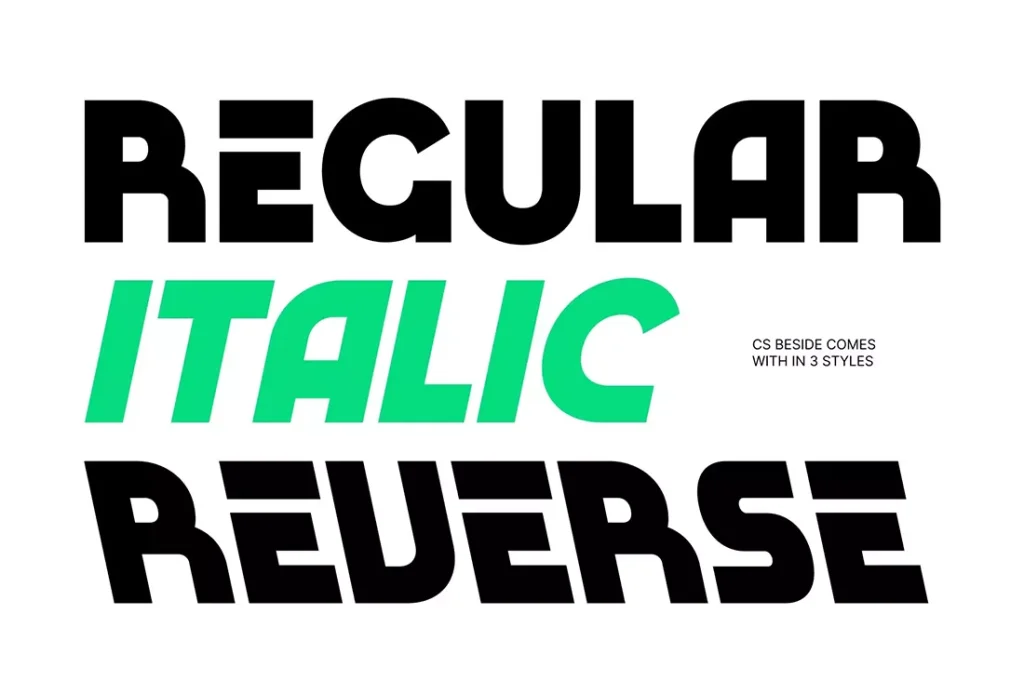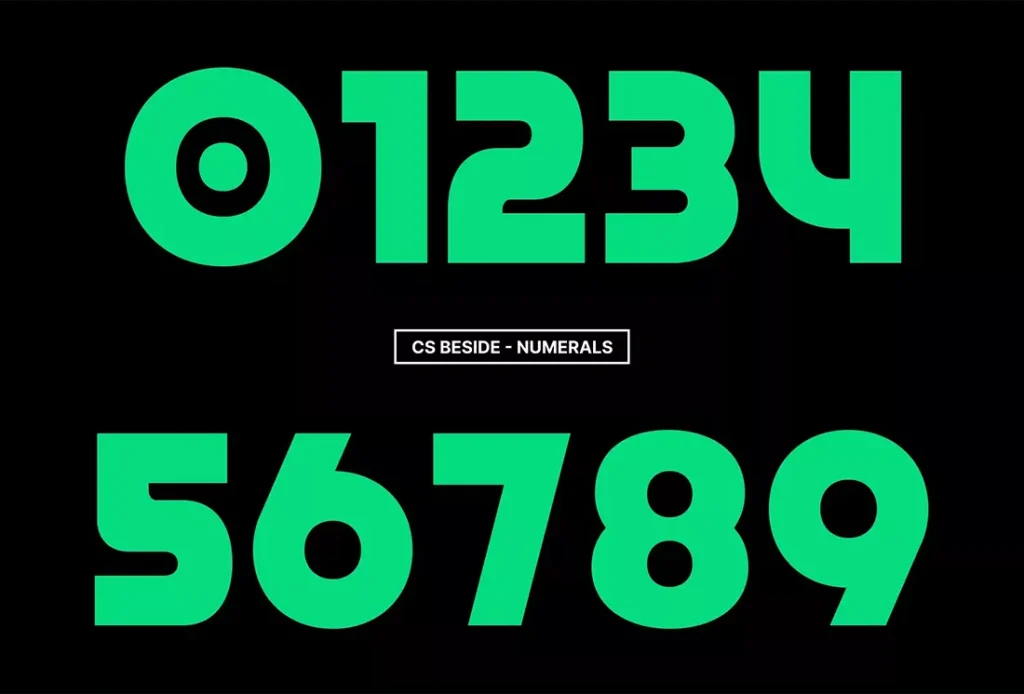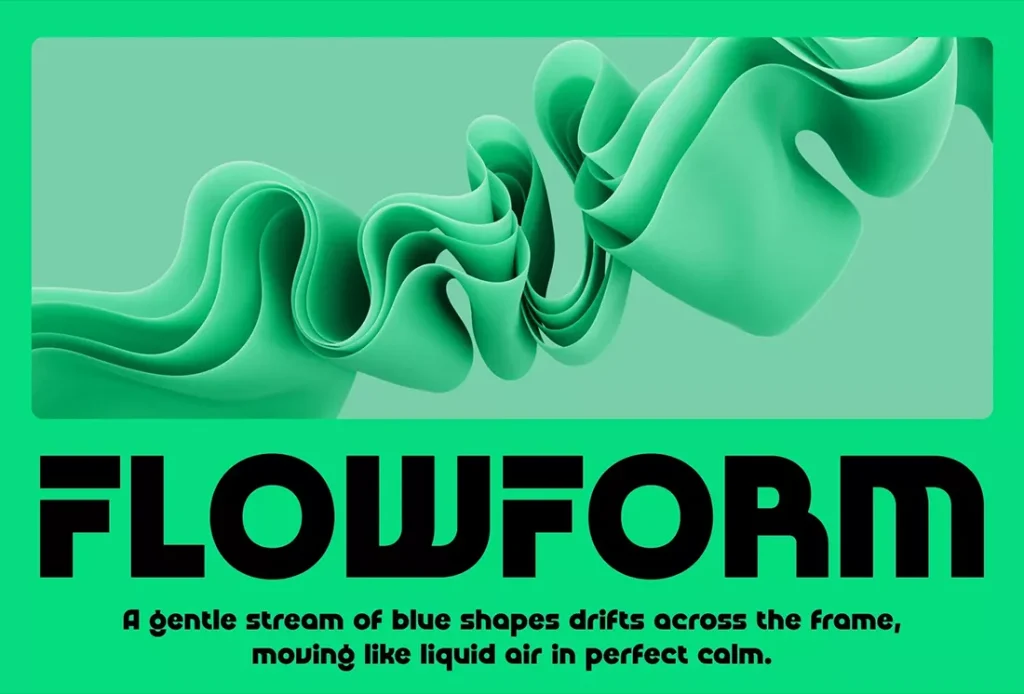
فونت نمایشی با وزن بولد و بزرگ با تاثیر دیجیتالی و آینده نگر برای جلب توجه از طریق حرف قوی و تاثیر گذار برای پروژ های گرافیکی مناسب است
دانلود فونت Font Cs Beside فونت نمایشی پررنگ با تأثیر دیجیتال آینده‌نگر، حضوری قدرتمند در قالب نمایش پیکسلی. این یک فونت نمایشی پررنگ است که برای جلب توجه از طریق حروف قوی و تأثیرگذار ساخته شده به سبک پیکسلی طراحی شده است. ساختار محکم و وزن سنگین آن، یک ضربه بصری فوری ایجاد می‌کند، در حالی که ساختار پیکسلی، یک شخصیت متمایز دیجیتال و رترو-آینده‌گرا به آن اضافه می‌کند. این ترکیب باعث می‌شود فونت قدرتمند، پرانرژی و از نظر بصری چشمگیر به نظر برسد، مناسب برای طرح‌هایی که باید فوراً برجسته شوند.